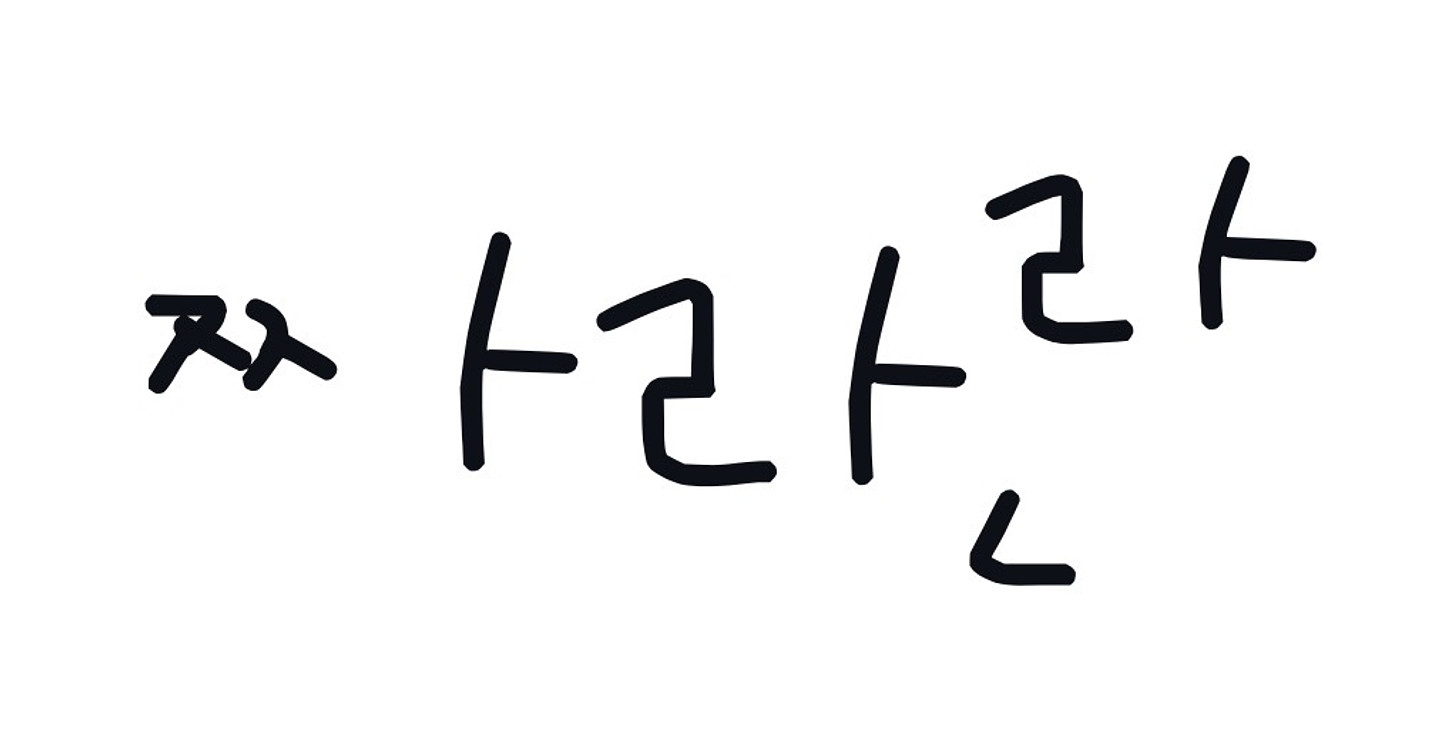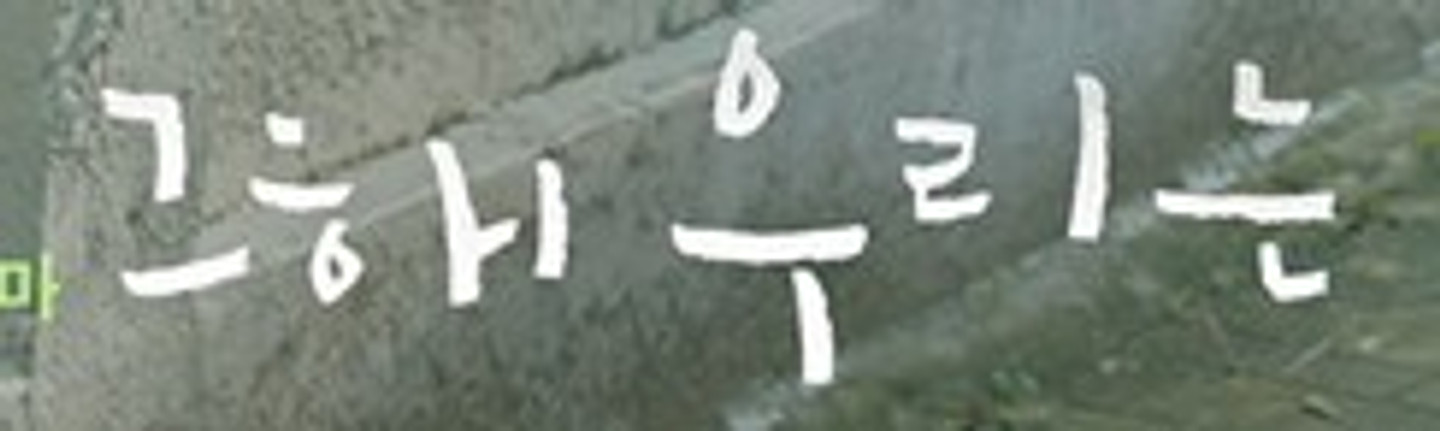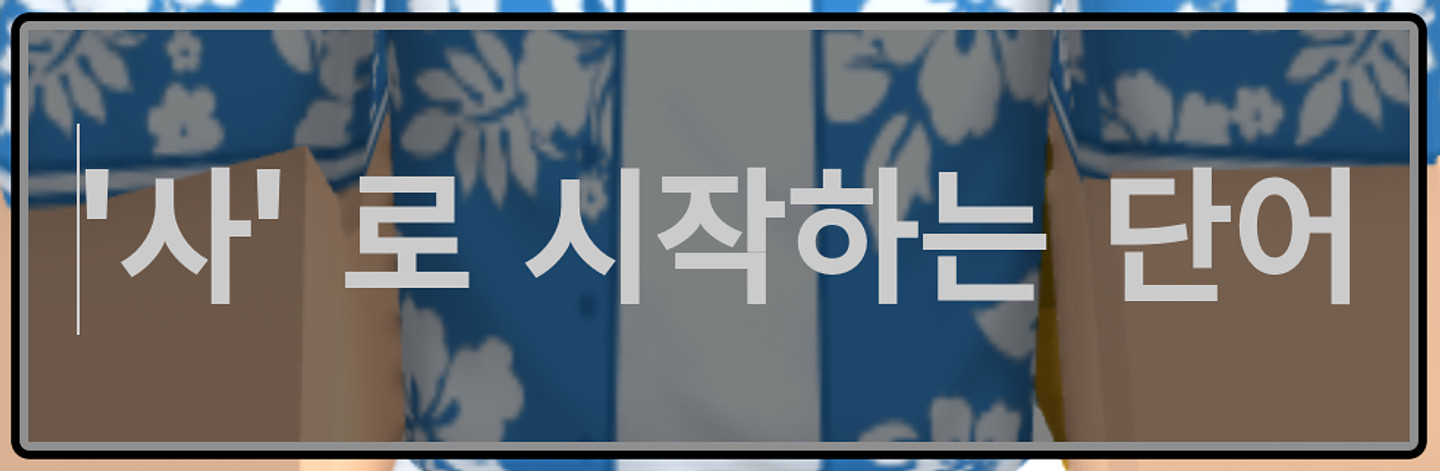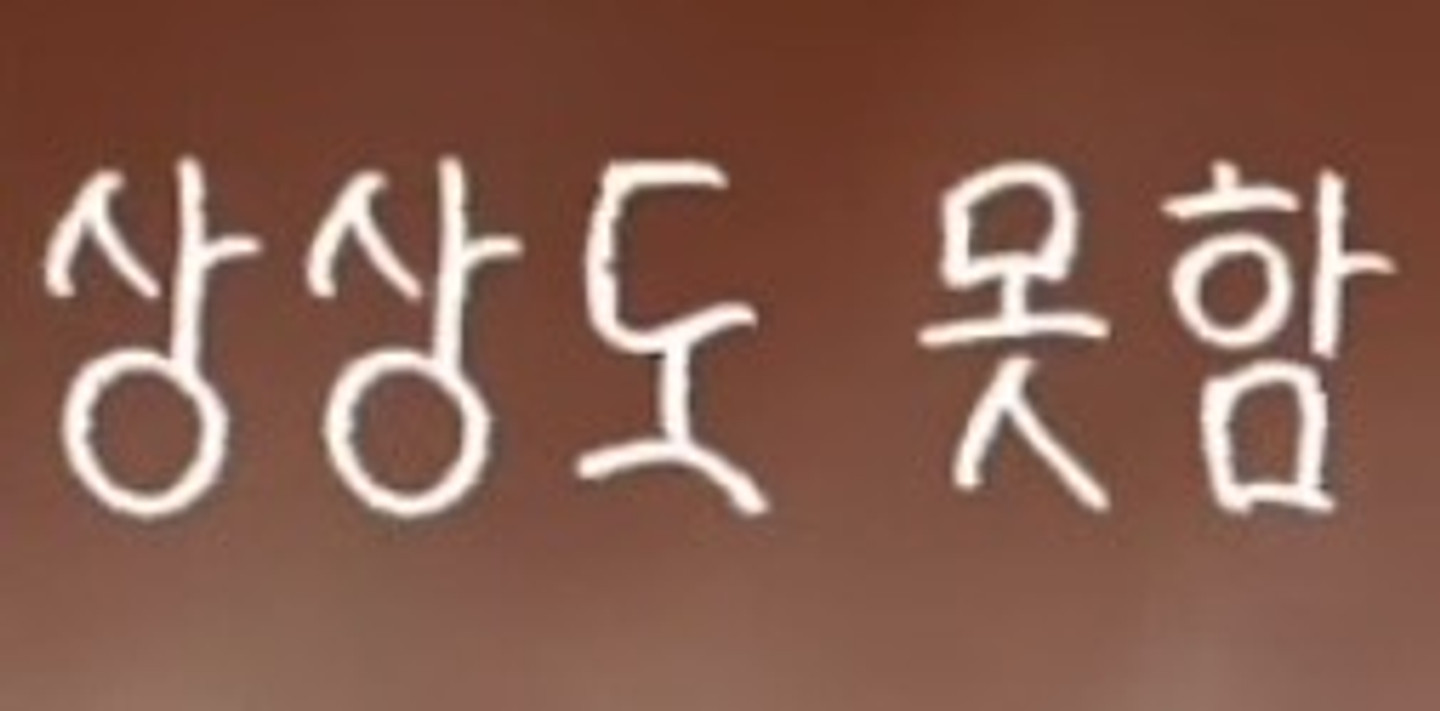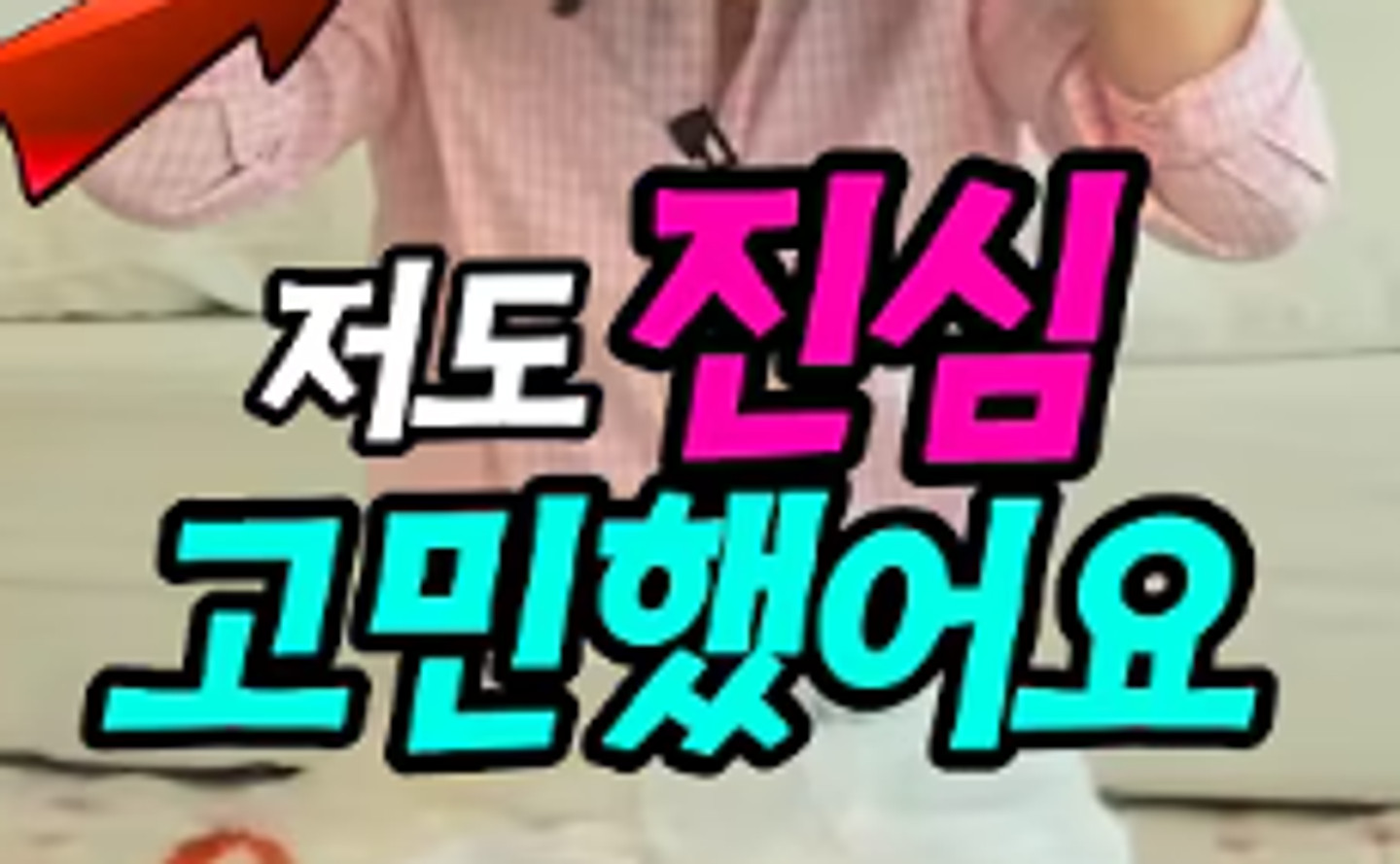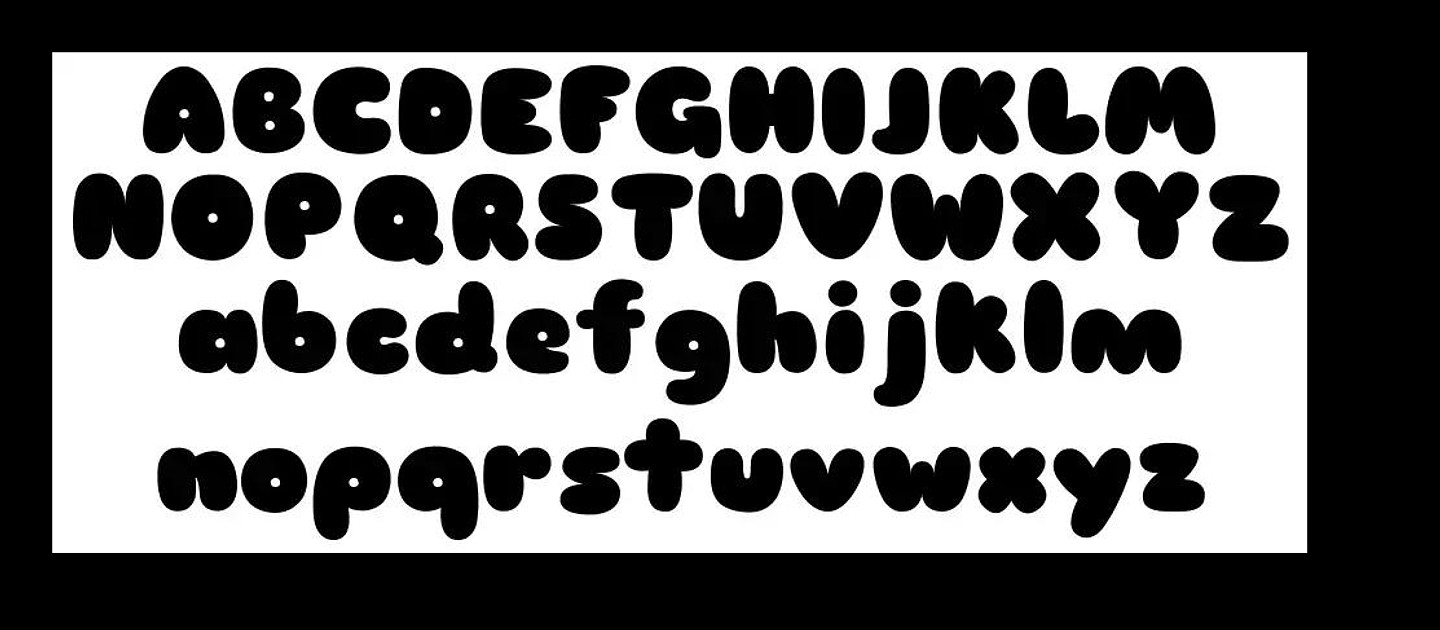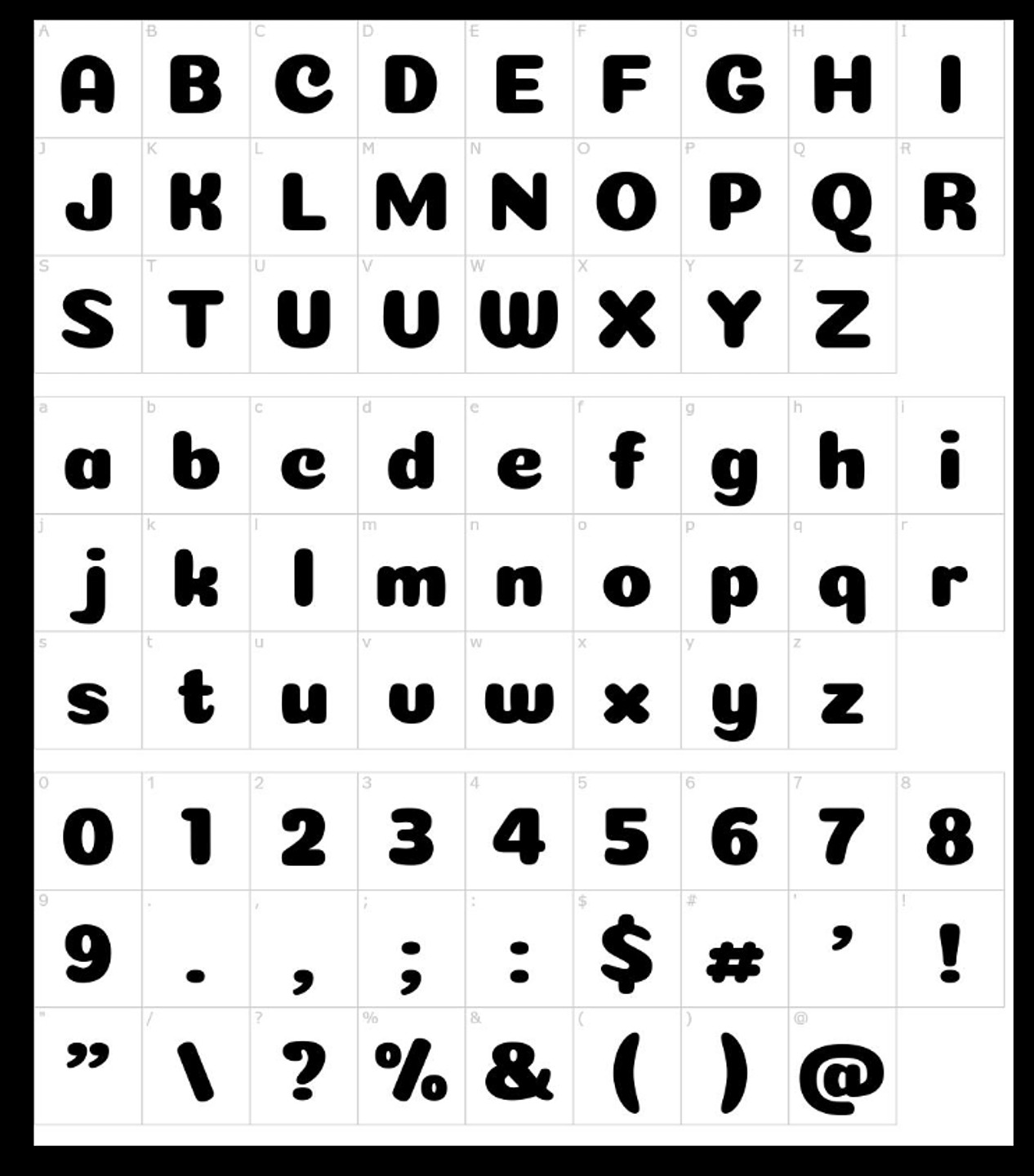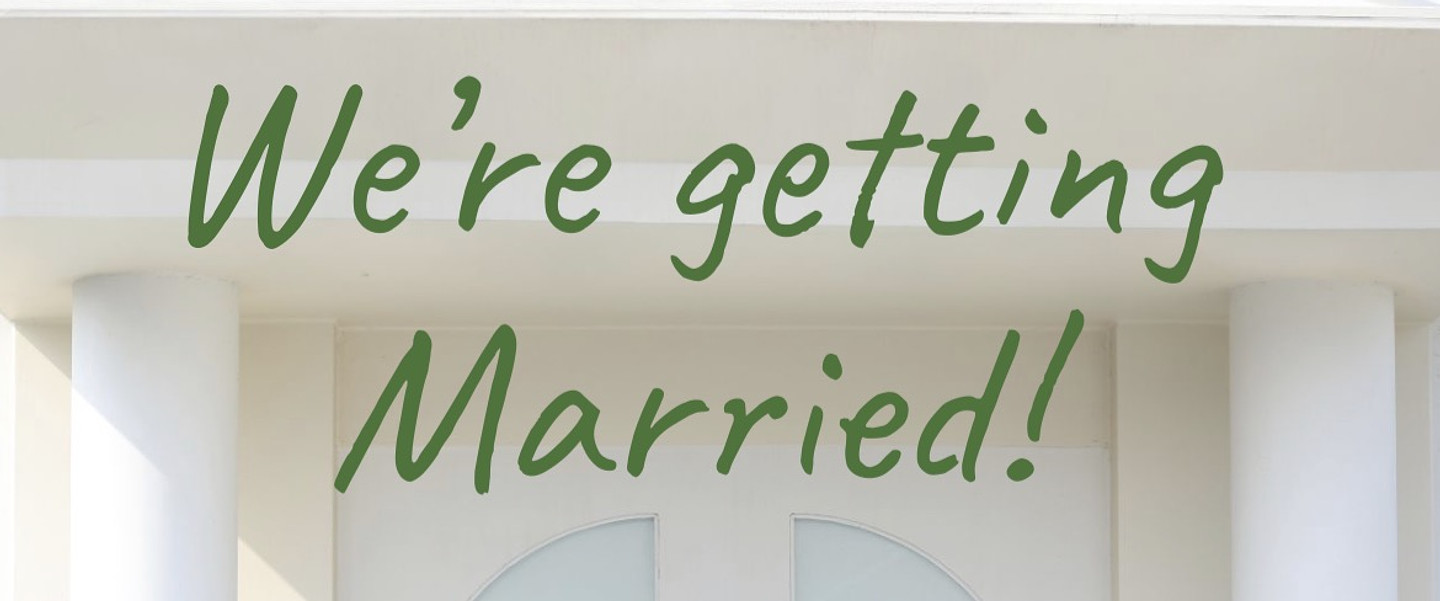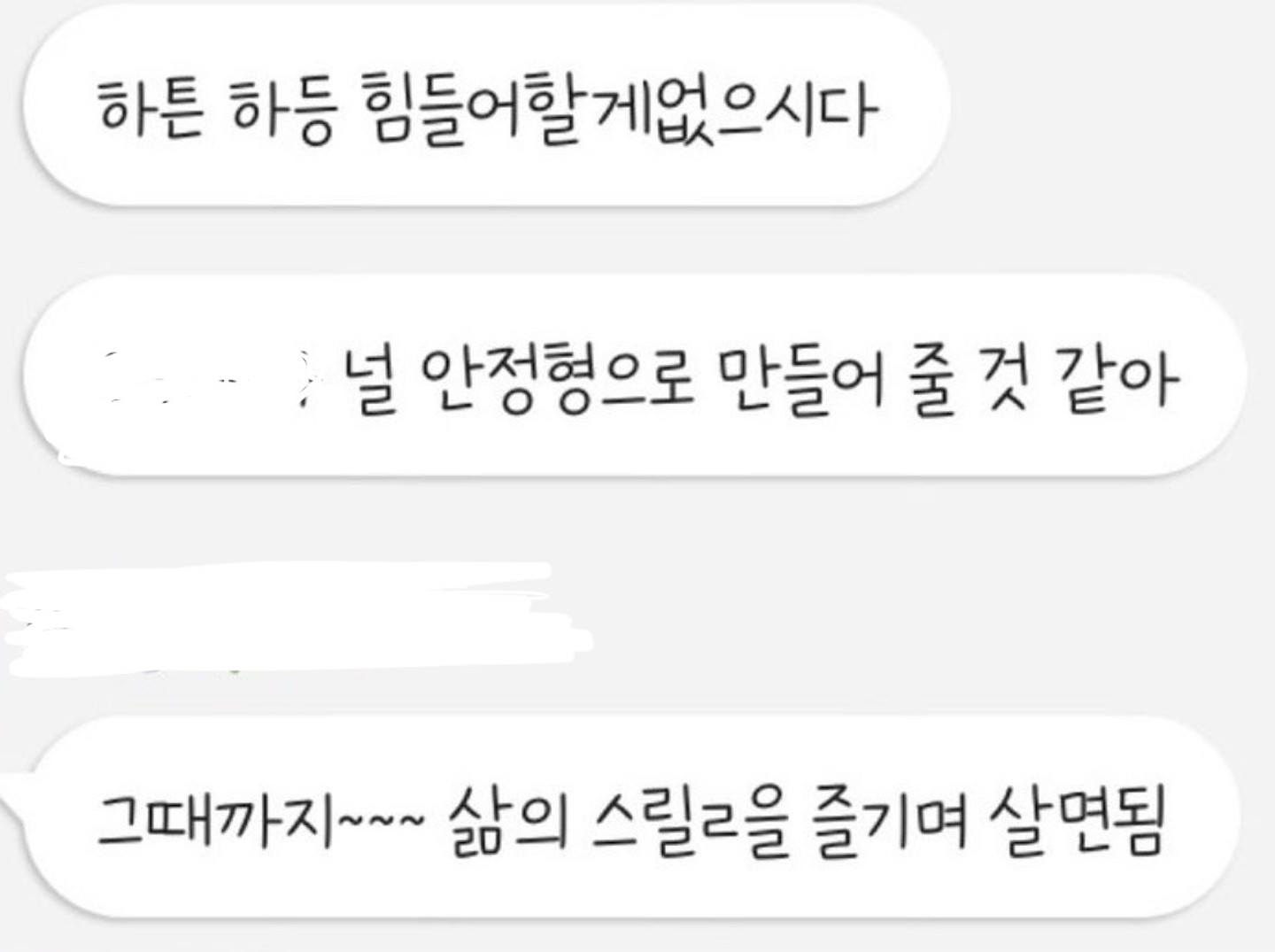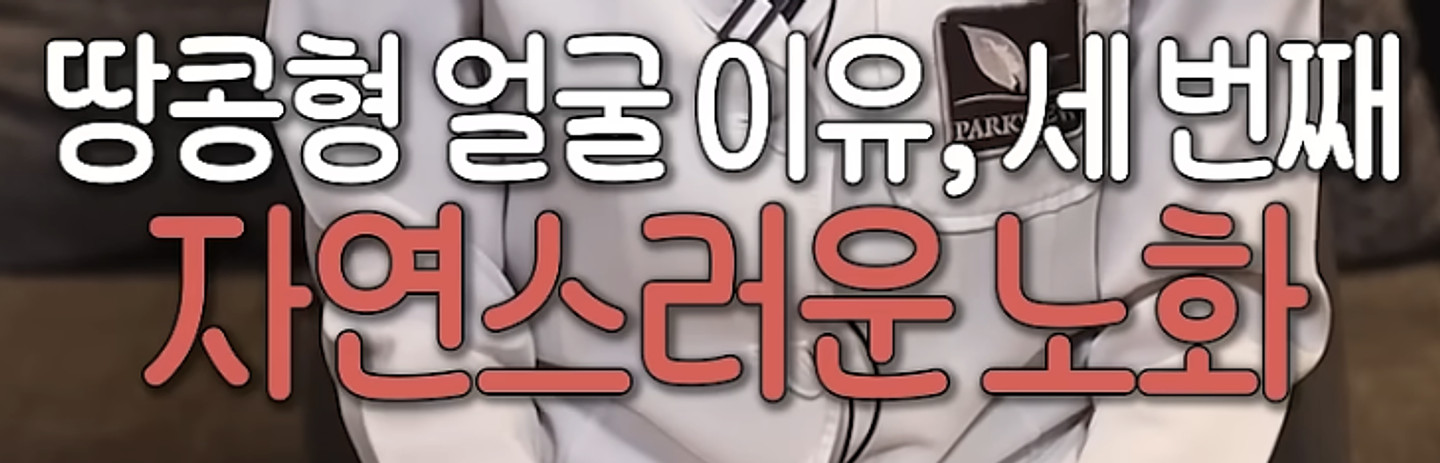
유튜버 혠이님 영상에 나오는 폰트 궁금해요 뭘까요? ㅠㅠ
폰트 뭔지 알 수 있을까요?
Sk 와이번스 시절 마킹 폰트가 궁금합니다. 만약 없다면 비슷한 폰트라도 알려주셨으면 감사할것같아여
폰트 찾을 수 있을까요? 그냥 인터넷에서 주운 이미지인데.. 괄호가 완전 둥그스름 형태가 아니고 살짝 각이 있는 특징이 있습니다 ㅠㅠ
혹시 어떤 폰트인지 아실까요?ㅠㅠㅠ